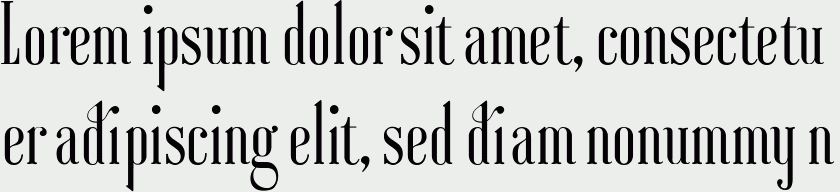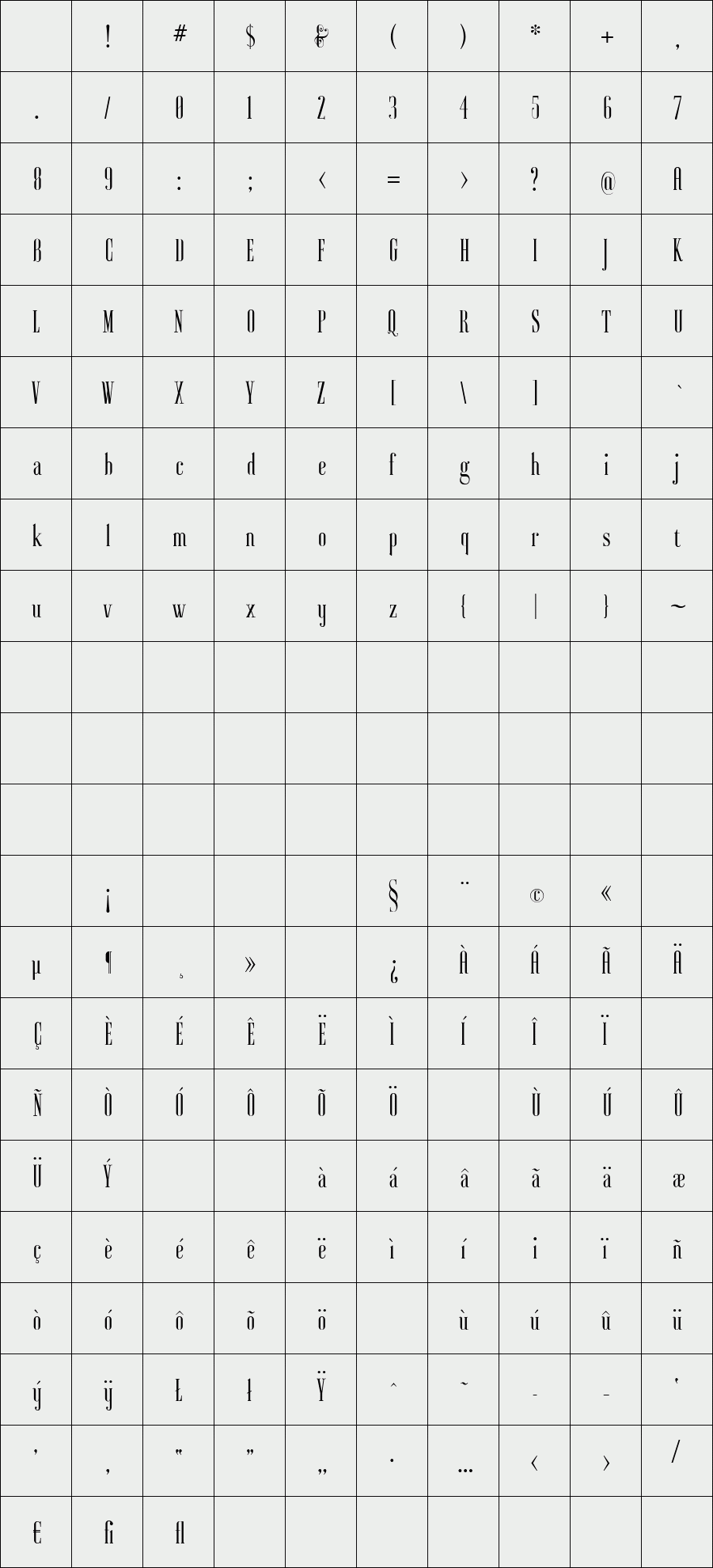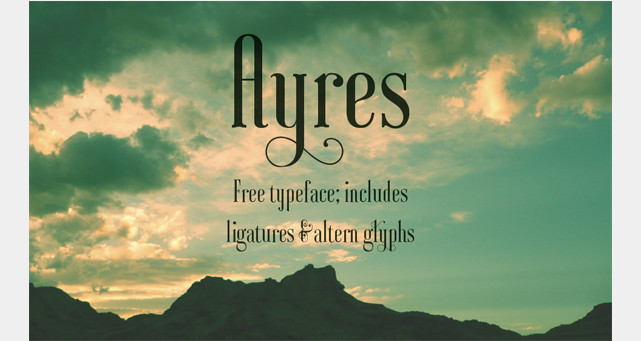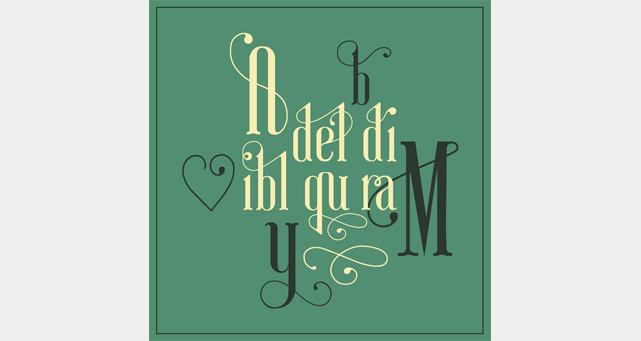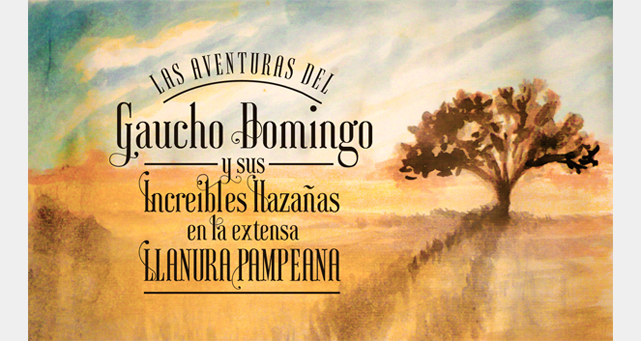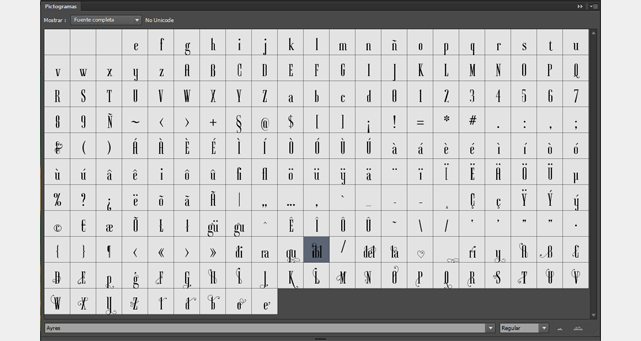
Ayres
Ayres es una fuente condensada, para uso display. Esta es la versión final, pero siempre pueden haber mejoras, acepto sugerencias y comentarios!!
Dispone de ligaduras y alternates para su uso decorativo.
Designer: Mariel Gornati